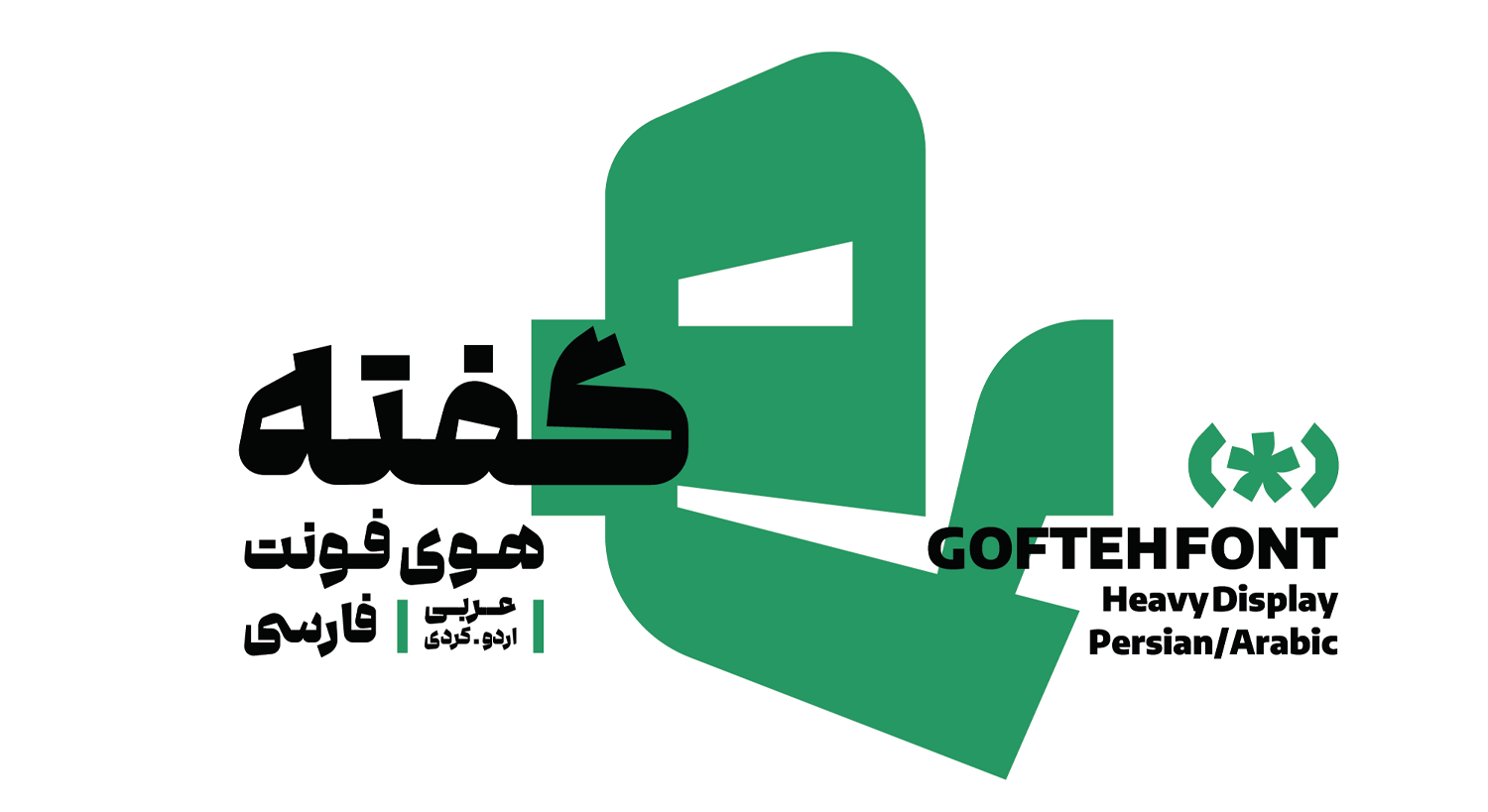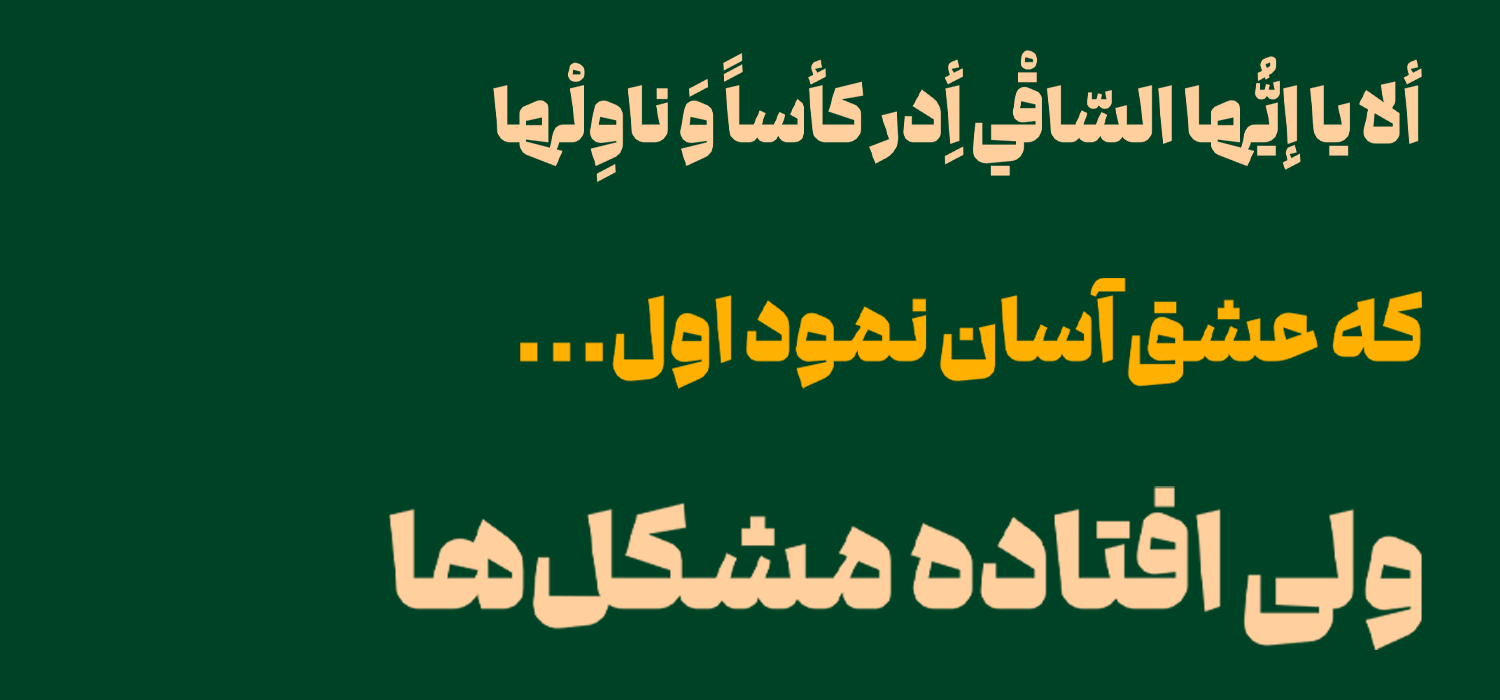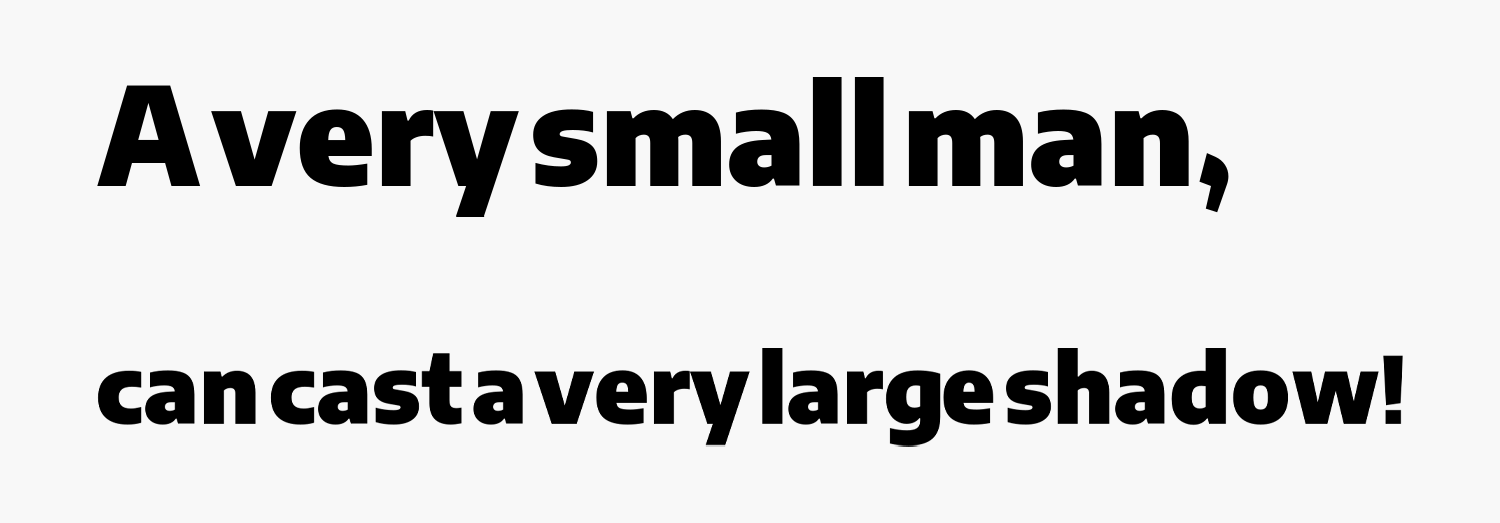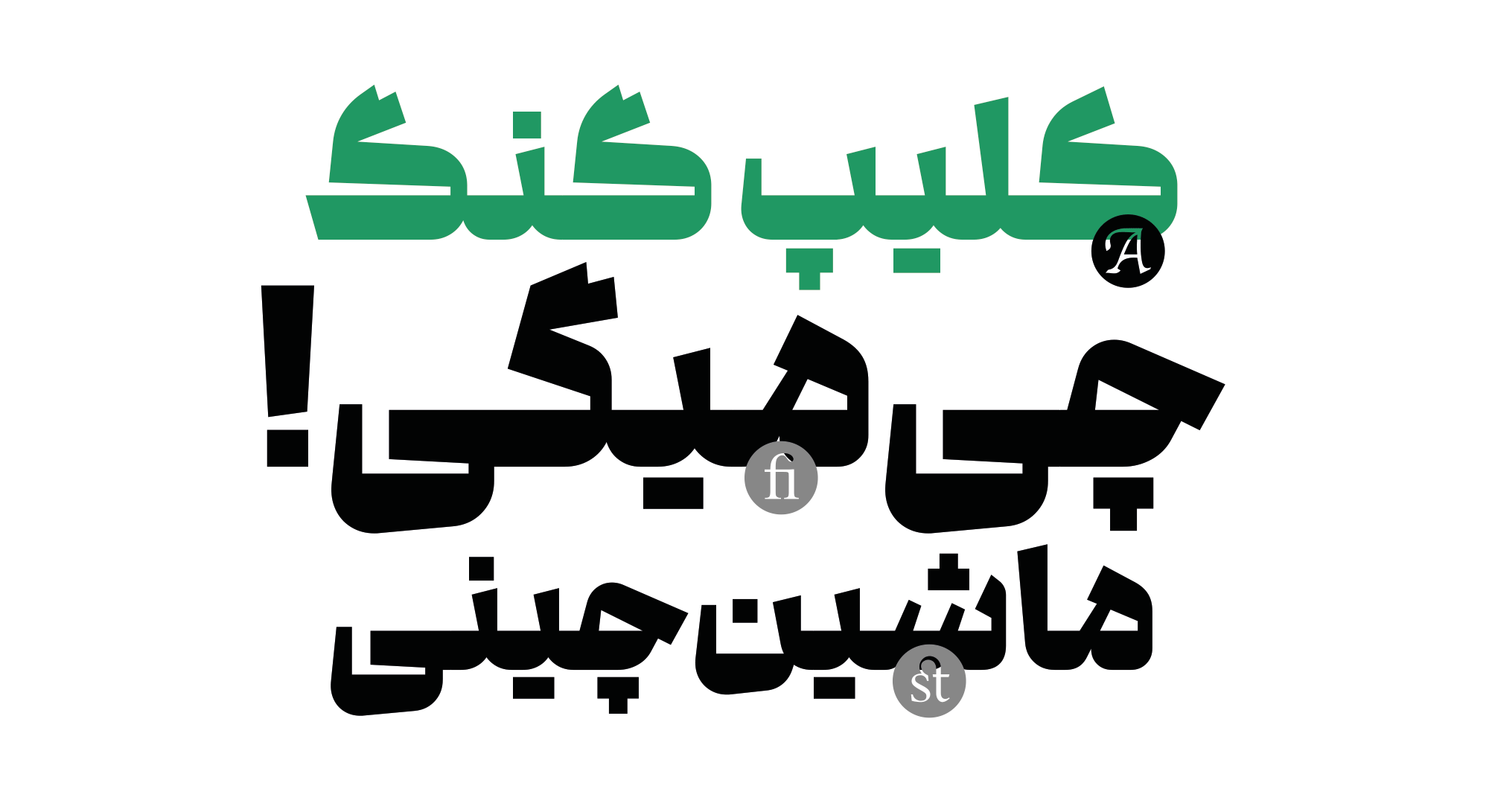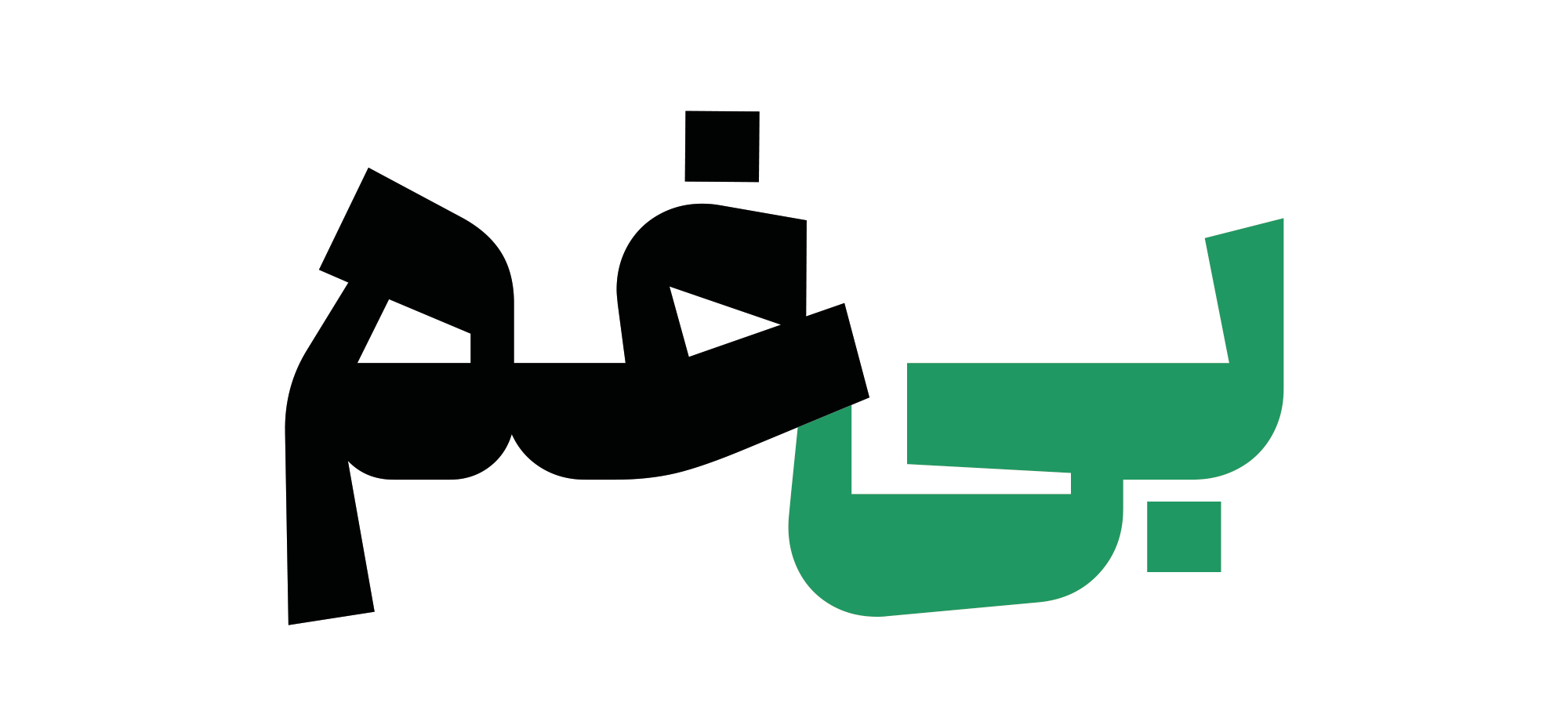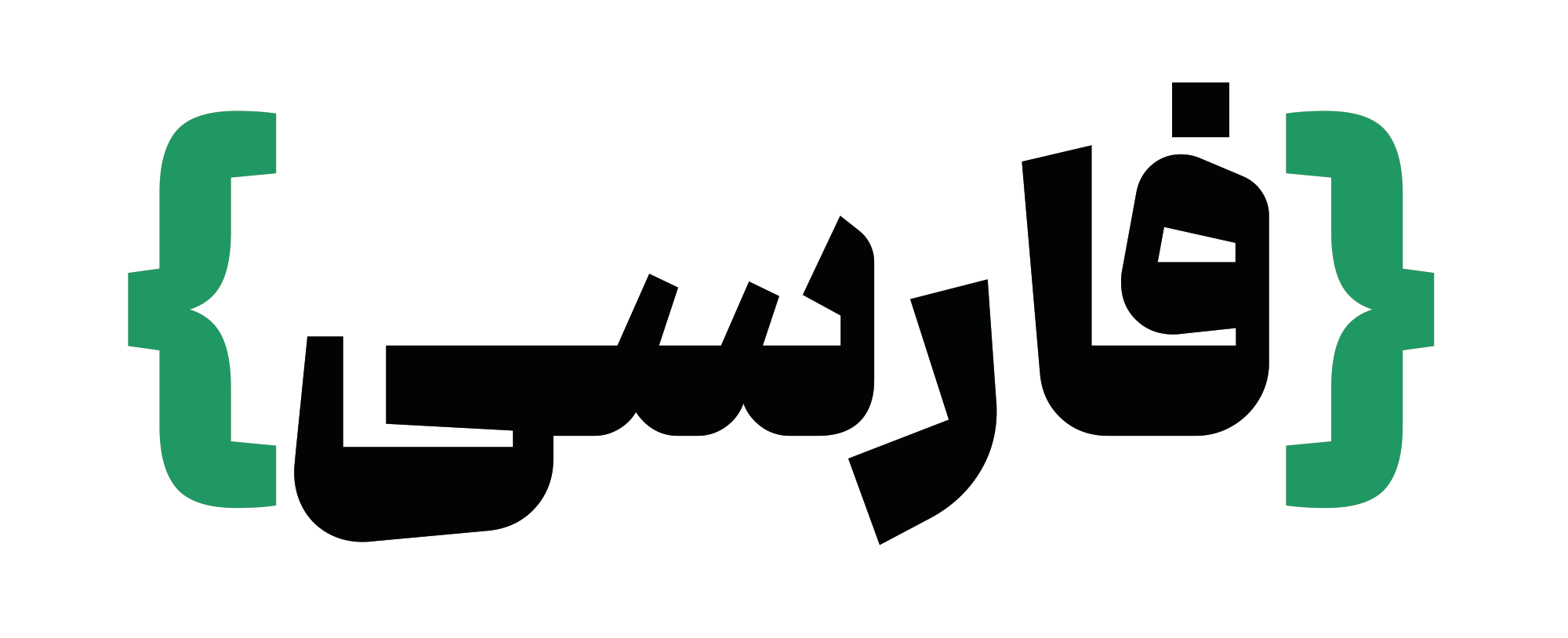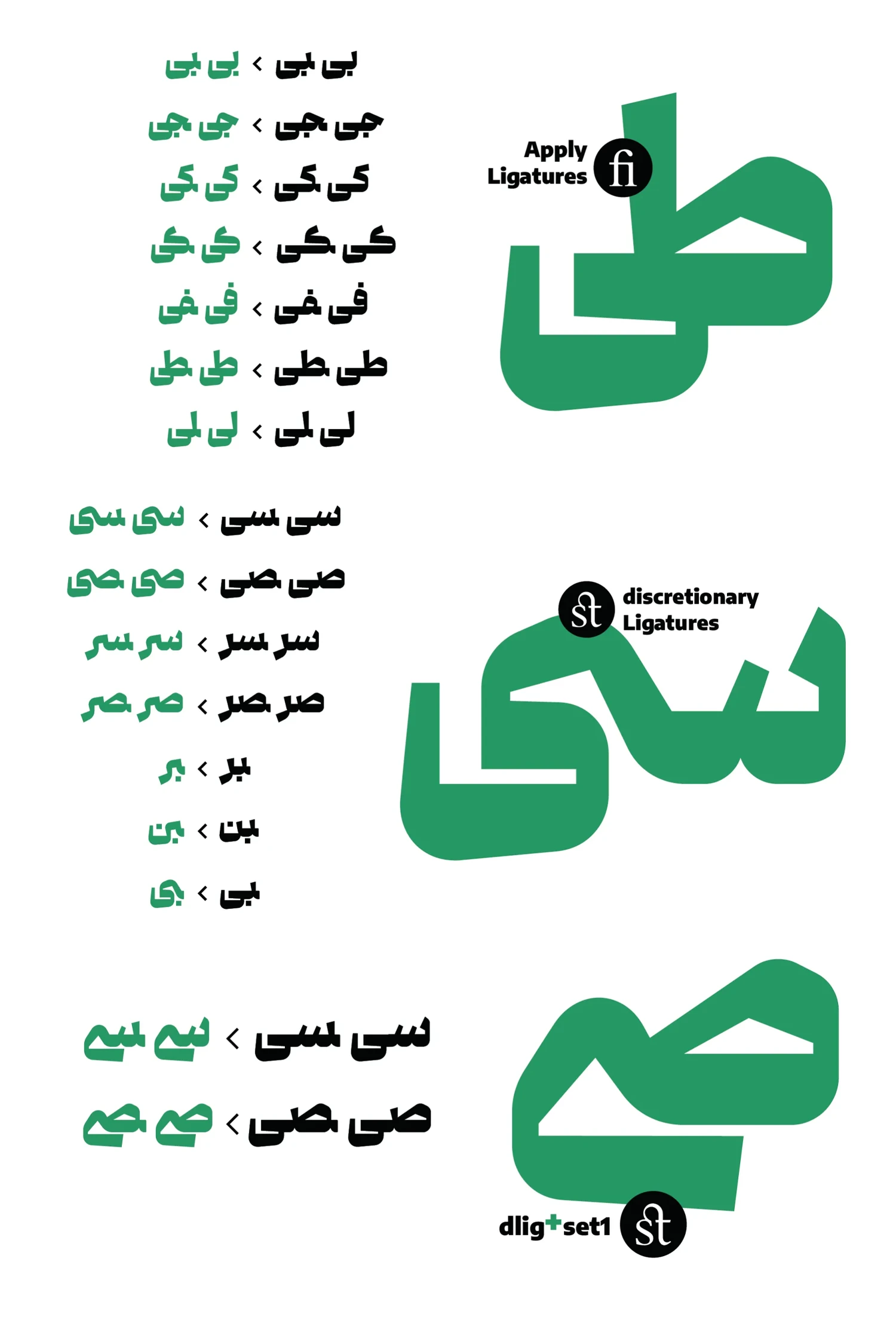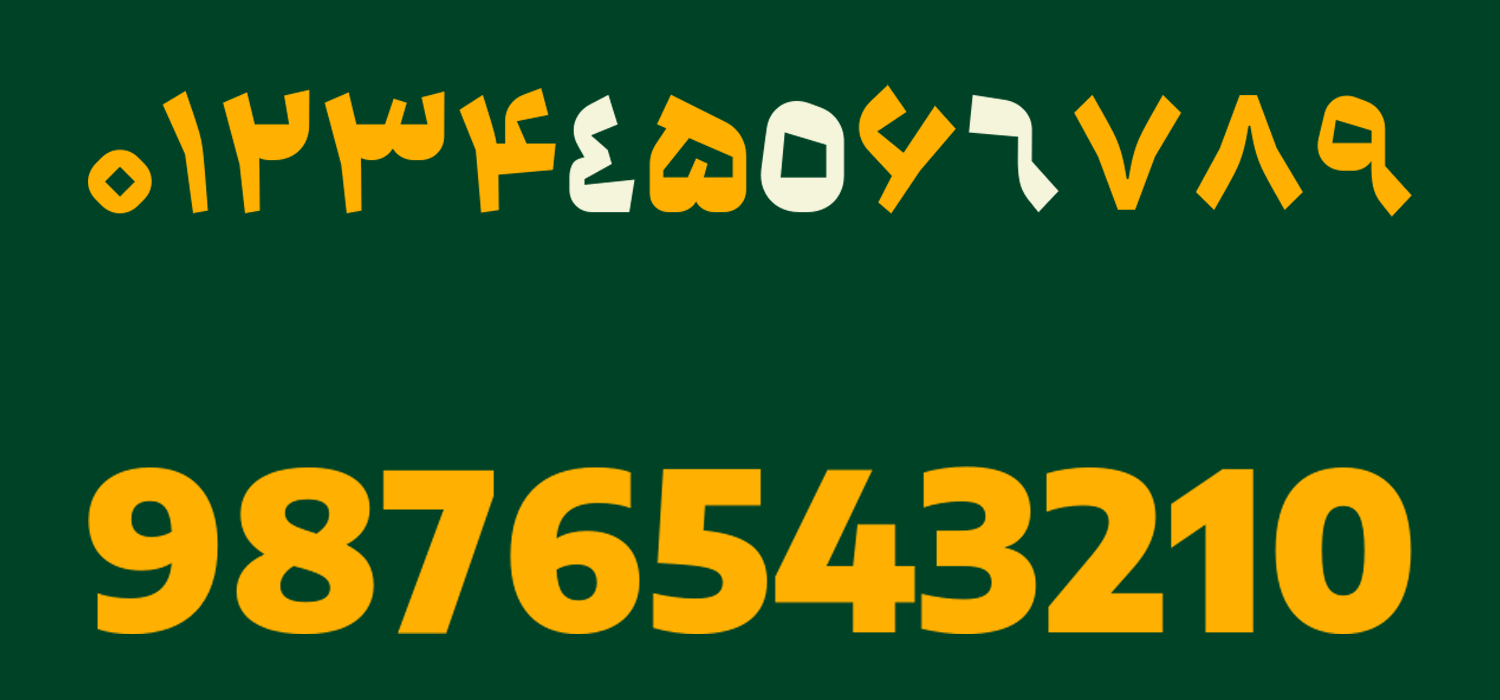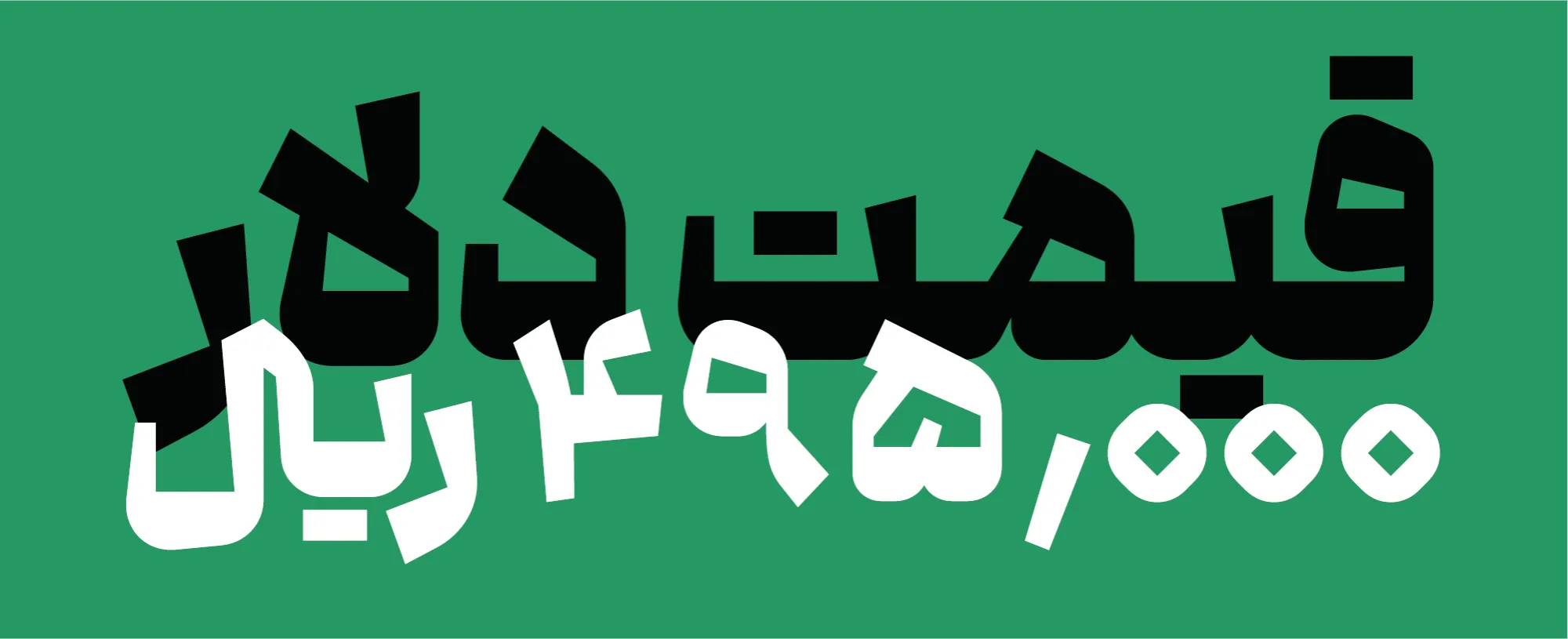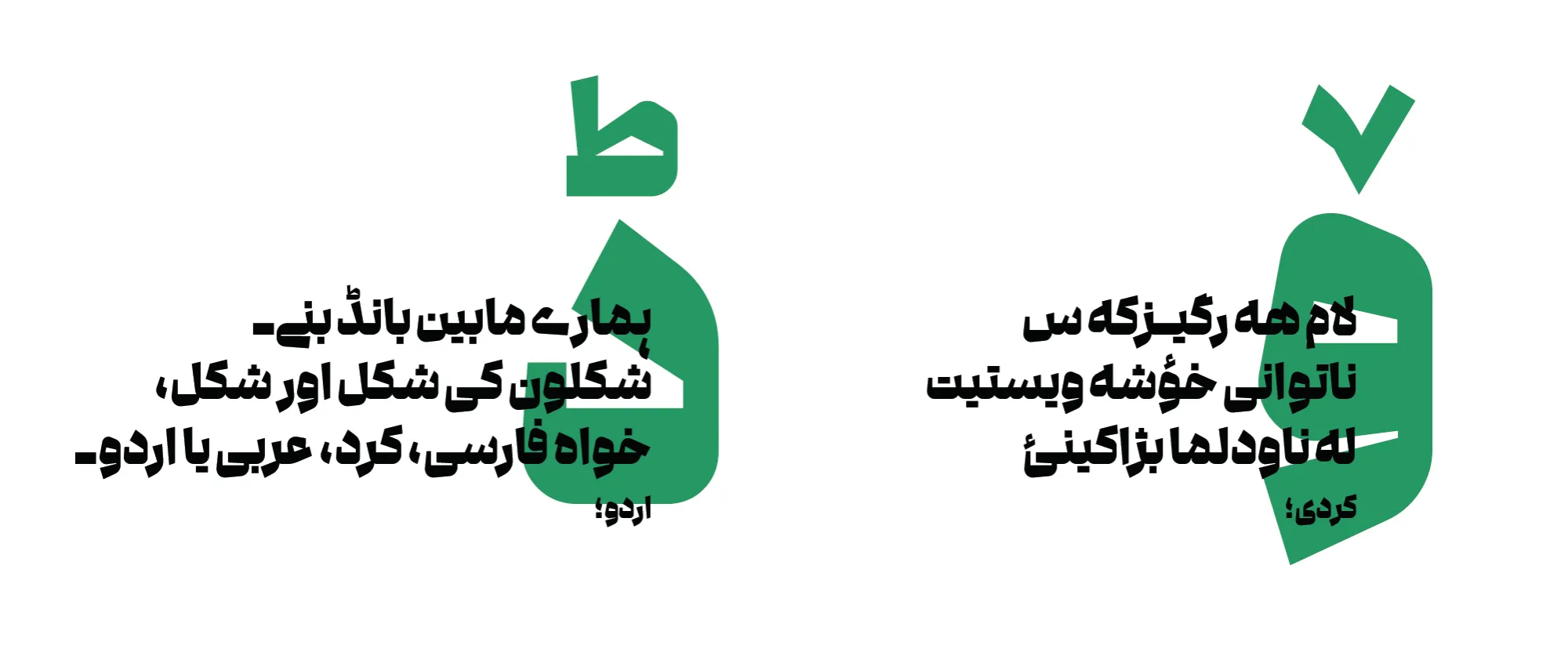
فونت گفته (Gofteh)
| طراح | علیرضا نعمت الهی |
فونت گفته (به انگلیسی: Gofteh) در گروه فونتهای نمایشی دارای ساختار کاملا هندسی است که برای استفاده در عناوین و لوگو تایپ توصیه میشود. از این قلم میتوانید در حوزههای تبلیغاتی بهترین استفاده را ببرید که در فضای دیجیتال برای تولید محتوا، ساخت انواع بنر و اسلایدر، ساخت موشن گرافیها و… بهترین خروجی را از خود برجای خواهد گذاشت. فونت گفته رایگان نبوده و با پشتیبانی از یک وزن، اما حروف جایگزین متعددی که دارد، در قالب یک بسته قابل خریداری است.
طراحی این قلم توسط علیرضا نعمت الهی صورت گرفته که آن را در یک وزن Heavy طراحی کرده است. این تایپفیس اولین تجربه اجرایی این طراح است و امیدواریم که آثار بیشتری از وی ببینیم. گفته با ترکیبی از منحنیها و خطوط ایجاد شده که در بخشهای مختلف حروف گاها قطور بوده و گاه ظاهری استخوانی دارند.
قلم gofteh یک تایپفیس نمایشی سنگین با ظاهری آرتیستی و سرشار از روحیه خودنمایی است که از این قلم میتوانید در محیطهای تبلیغاتی و برای فونت عنوان استفاده کنید.
در اطراف سالهای ۹۹ چند حرف روی کاغذ طراحی کردم؛ که به نظرم حال و هوای خوبی داشت. یکسال بعد تصمیم گرفتم آن چند حرف را توسعه دهم اما بعد از چند هفته کار، نتیجه رضایتبخش نبود و فایل بایگانی شد!
تا اینکه سال ۱۴۰۲، پس از گذراندن کلاسهای استاد دامون خانجانزاده اتودها را از نو آغاز کردم و با تمرکز بیشتر روی کانسپت طراحی حروف اولیه فونت گفته طراحی شد.
علیرضا نعمت الهی؛ طراح قلم گفته.
این فونت از چندین زبان مختلف خاورمیانهای و لاتین پشتیبانی میکند که با توجه به نزدیکی به سایر قلمها در هر زبان میتوانید به صورت ترکیبی از آن استفاده کنید. این قلم شباهت نسبتا نزدیکی به فونت صنعت دارد با این تفاوت که از نظر وزنی نازکتر و از نظر طراحی دارای روحیهای نرمتر است.
سبک طراحی و وزن فونت گفته
فونت گفته برای طراحی پوستر، تولید محتوا و تایپوگرافیهای نمایشی و متنهای کوتاه مناسب است. از همینرو دارای یک وزن ضخیم Heavy میباشد که ساختاری ضخیم و سیاه به قلم داده است.
کلیه ساختار حروف در این قلم دارای ساختاری هندسی هستند و ضخامت در سرتاسر حروف نیز متفاوت است طوری که فونت از نظر ضخامت دارای درجه خاصی در تمامی حرفها میباشد که ضخامت در بخشهایی لاغز و در بخشهای دیگر به مرور که درجه حروف (بهویژه در خطو قائم و مورب) تغییر میکند روند افزایشی یا کاهشی به خود میگیرد.
پشتیبانی از 5 زبان متنوع
فونت فارسی گفته محدود به این زبان نبوده و بهلطف رسمخط فارسی بودن زبانهای عربی، کردی و اردو امکان استفاده از این قلم را در این زبانهای خاورمیانه ای دارید که پشتیبانی کاملی از زبانهای ذکر شده دارد.
تمامی حروفی که به صورت مشترک در این زبانها قابل استفاده هستند دارای گلیف اختصاصی بر اساس زبان صفحه کلید هستند و علاوه بر این حروفی نظیر «ك، ي، ة، ؤ، ئ» برای زبان عربی یا حروف «ﮧ، ﮩ، ے» در زبان اردو که دارای شکل متفاوتی هستند را نیز پشتیبانی میکند.
از حرف متفاوت «ے» پایانی زبان اردو بهعنوان حرف جایگزین استفاده شده است که به زیباتر کردن کلمات کمک خواهد کرد.
با دانلود فونت گفته برای فتوشاپ میتوانید از طریق تنظیمات اپنتایپ به این حروف جایگزین دسترسی داشته و همچنین با پشتیبانی که از اعداد فارسی و عربی دارد، متناسب با نیاز خود از گلیفهای مورد نظر استفاده کنید.
فونت گفته انگلیسی در این تایپفیس فاقد طراحی اختصاصی بوده و برای حروف انگلیسی از فونت Encode Sans که دارای طراحی نسبتا نزدیک به قلم بوده و دارای لایسنس OFL میباشد، استفاده شده است.
حروف جایگزین فونت گفته با تنوع بالا
حروف جایگزین در فونت گفته امکان تایپ متفاوت کلمات را به شما خواهند داد تا بدون نیاز به استفاده از نرمافزارهای گرافیکی مثل فتوشاپ و ایلاستریتور، بتوانید در طراحی خود خلاقیت بهخرج دهید. با توجه به کاربرد این قلم که برای عناوین و فونتهای تبلیغاتی مناسب است، این نوع ترکیبات میتواند روی جلب توجه مخاطب موثر باشد.
به عنوان نمونه مشابه تصویر بالا میبینید که حروف و ترکیبات «ک، گ، ی» در حالتهای مختلفی که در ابتدا، انتها یا میانه کلمات باشند در چند حالت مختلف قابل تایپ کردن هستند.
از آنجا که در یک جمله میتوان برخی کلمات را با این ساختار متفاوت تایپ کرد که بهراحتی کاربر نیز در همان نگاه اولیه و بهدور از اینکه نیاز باشد جمله را بخواند متوجه این تفاوت میشود؛ استفاده از این حالت در کارهای تبلیغاتی موجب جلب توجه و خوانش متن خواهد شد.
ترکیب دیگر قلم از نظر حروف جایگزین برای حرف «میم» است که در انتهای کلمات میتوانید آن را به صورت پیوسته یا ناپیوسته مشابه تصویر زیر تایپ کنید.
حرف «ی» جایگزین در فونت گفته نیز با توجه به اینکه حرف قبلی آن چه باشد، قابلیت تایپ به شکلهای متفاوت دیگری را دارد که نمونه آن را در تصویر زیر میبینید.